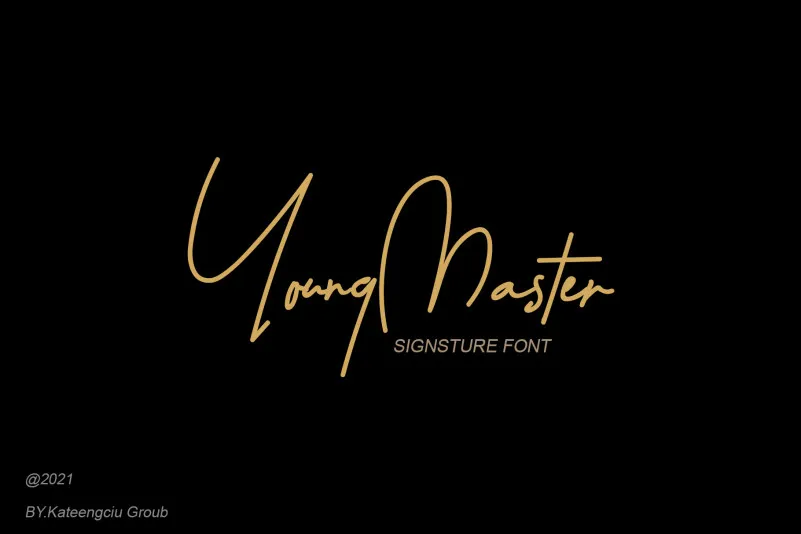
Young Master Font – Download Grátis
Esta é uma fonte à mão escrita que transmite emoções suaves e versatilidade. Suave e descontraída ao mesmo tempo, ela traz alegria e conforto para qualquer projeto. Esta fonte transformará seus ideias de projeto em obras de arte belas e únicas. Experimente esta linda fonte e descubra suas inúmeras variações possíveis. Sempre com um toque jovial e divertido, ela será uma companheira perfeita para todos os tipos de criação visual. Descubra como Young Master Font pode tornar seu trabalho ainda mais especial e único.